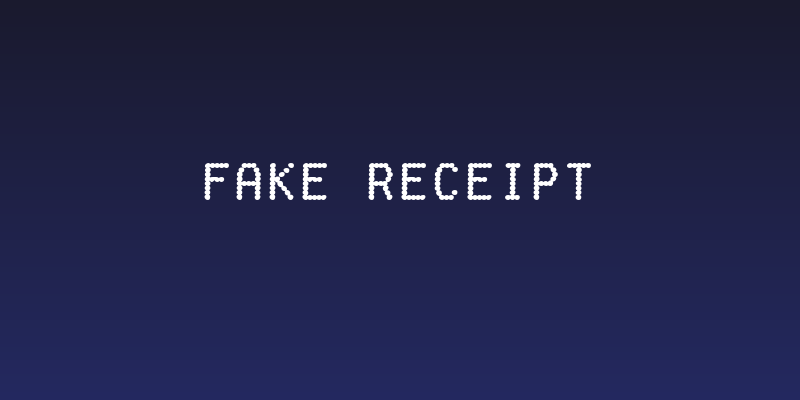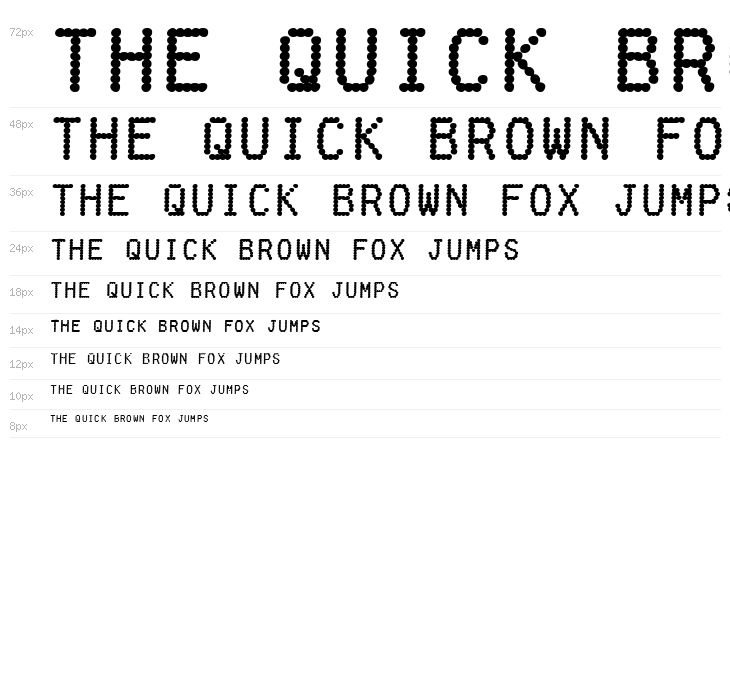
Fake Receipt Font
✎ Pixel
| Kategorien | Pixel |
| Gesamtstil | Vintage |
| Anwendungsfall | Logos, Headlines, Digital Art |
| Vorgeschlagene Projekte | Ideal for retro-themed designs, tech-related projects, digital art, and any creative work that seeks to evoke nostalgia for early computing and digital displays. |